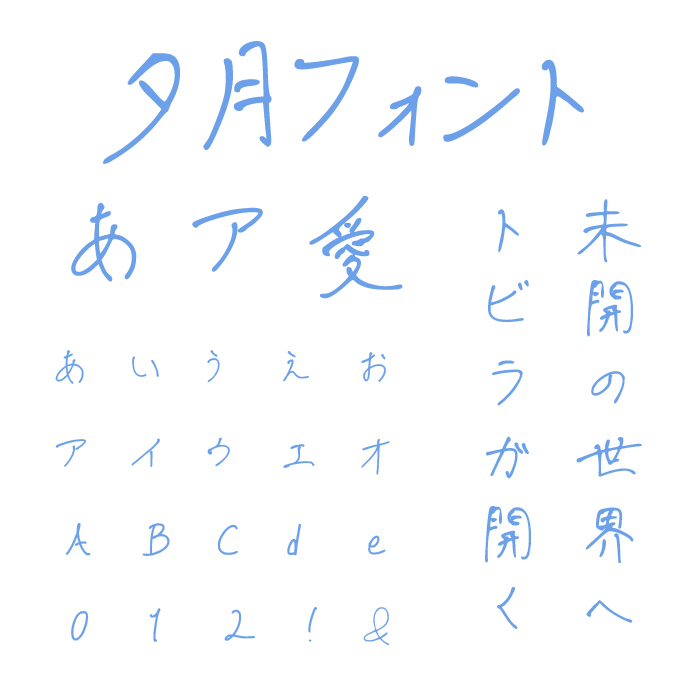
夕月フォントは、細筆でさらっと書いたような線と、長めに伸びる終筆が特徴の手書きフォントです。
かすかな揺れが残っていて、手で書いた文字ならではの温かさが伝わります。
日記やエッセイ、旅の記録などに使うと、落ち着いた雰囲気が出ます。俳句や短歌の本文やキャプションにもよく合い、しみじみとした気分を演出できます。英字も自然に馴染むので、旅行を題材としたテーマなどにもぴったりです。
背景は淡い色や余白を広めに取ると効果的です。行間を広くして文字に呼吸をさせると、より静かで柔らかい雰囲気になります。